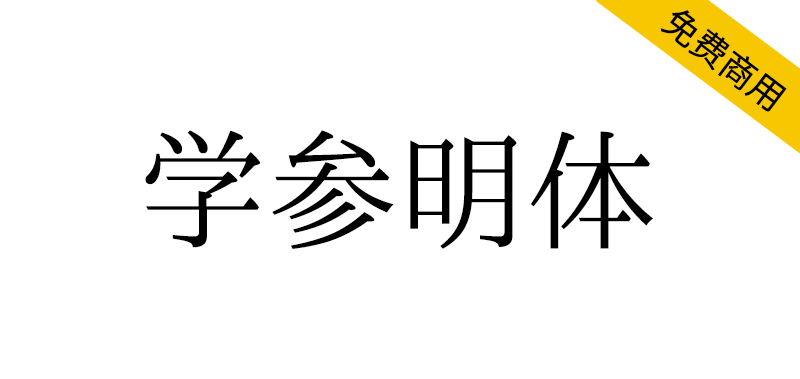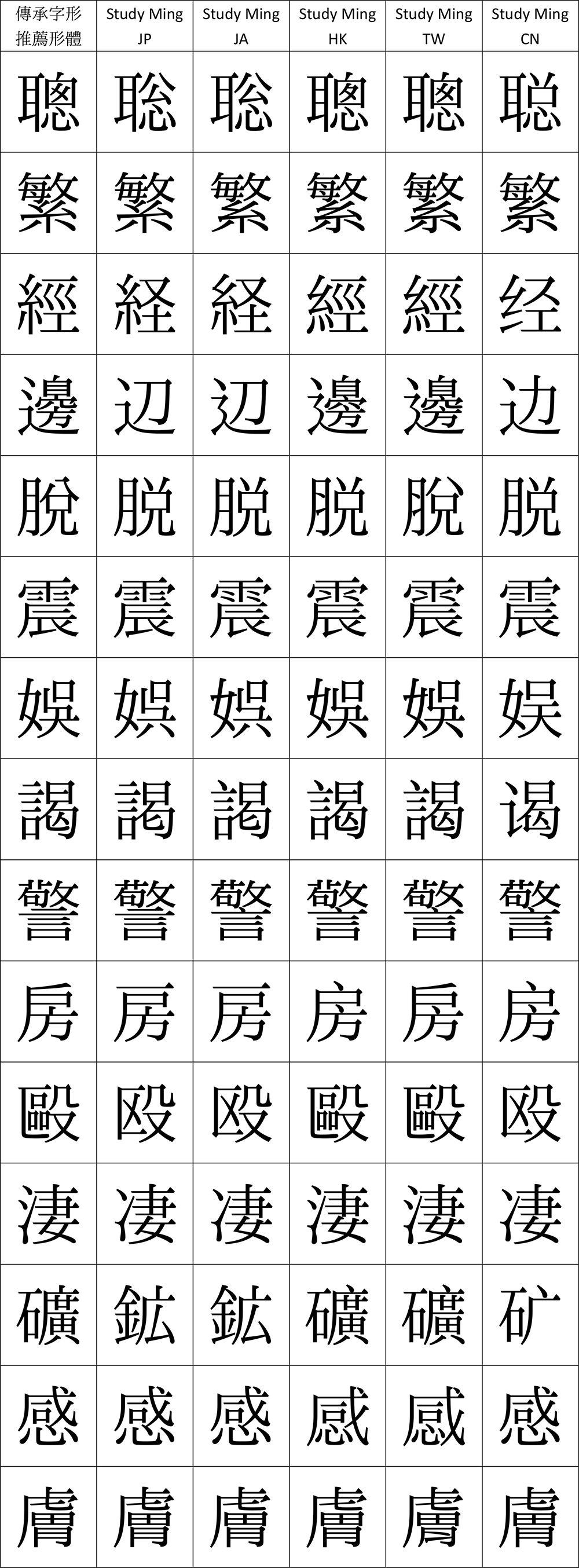
学参明体是一款汉字硏究计划开源字体,因汉字字形之硏究所需,目前没有符合硏究需求的字体可用,故启动本计划,制作符合需求之字体,字体成品如下:
Study Ming JP(学参明朝体 日本 印刷):主要依《常用汉字表》(东京:文化庁,2010年),以及《常用汉字表の字体・字形に关する指针(报告)》(东京:文化庁,2016年)中的明朝体字形,检校、修改当中常用字的汉字字形。
Study Ming JA(学参明朝体 日本 教科书):主要依《常用汉字表の字体・字形に关する指针(报告)》(东京:文化庁,2016年)中的教科书体字形﹐并参考表中的手书文字例子字形,以及モトヤ、モリサワ、イワタ等字体厂商的学参明朝体,检校、修改当中常用字的汉字字形。
Study Ming HK(学参明体 香港):主要依《常用字字形表》(香港:香港特别行政区政府教育局课程发展处中国语文教育组,2012年)及《香港小学学习字词表》(香港:香港特别行政区政府教育局课程发展处中国语文教育组,2007年),并参考《常用字字形表(二零零年修订本)》(香港:香港教育学院,2000年)和《香港电脑汉字参考字形》(香港:香港特别行政区政府政府信息技术总监办公室、公务员事务局法定语文事务部,2017年),检校、修改当中常用字的汉字字形。
Study Ming TW(学参明体 台湾):主要依《国字标准字体宋体母稿〈教育部字序〉》(台北:教育部普通话推行委员会,1998年),并参考《国字标准字体楷书母稿〈教育部字序〉》(台北:教育部普通话推行委员会,1998年)、《常用国字标准字体表》(台北:教育部,1982年),检校、修改当中常用字的汉字字形。
Study Ming CN(学参明体 中国):主要依《通用规范汉字表》(北京:教育部、国家语言文字工作委员会,2013年),检校、修改当中常用字的汉字字形。
为方便不同语系的操作系统使用,避免在其他语系的操作系统或软件中失效,这些字体的实际名字都只有英文名。所有字体的字高、行高皆与一点字坊的新一细明体统一,除了可以与之搭配使用,亦能与视窗操作系统预设的「细明体」搭配,不会出现行高改变之问题。